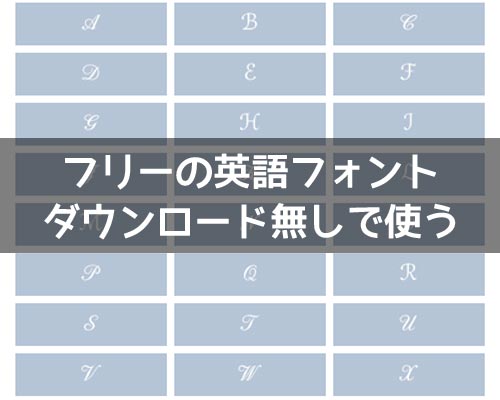
【フリー】英語フォントをダウンロードなしで使おう!オシャレなフォントも多数あります
英語フォントと聞くとフリーのフォントをダウンロードして利用するのを想像する方も多いですよね。
しかし最近ではダウンロードすら不要で英語フォントを使うこともできるのです。
特にツイッターやインスタなどのSNSなどで可愛い英語フォントやオシャレなフォントを使いたいと思っている方はダウンロードなんて必要ないんです。
英語フォントはダウンロード不要
【フリー】英語フォントをダウンロード不要で使おう!オシャレなフォントも多数あります
ダウンロードせずに英語フォントを使うのがどういう事かと言うと、絵文字のような感じでコピペして利用できるようになってます。
フォントをコピペするだけなのでダウンロードは不要。
好きなようにフォントを使うことができます。
どんなフォントが使えるの?
コピペで使える英語フォントにはどのようなフォントがあるのか気になる方もいるでしょう。
当サイトで確認しただけでも以下のような英語フォントがあります。
• 太字
• 太字斜体
• 斜体
• 明朝体
• 明朝体風
• ギリシャ文字
• ドイツ文字
• 花文字
• 筆記体
• 白抜き文字
• 手書き風文字
• 鏡文字
• 逆さ文字
上記の他にも様々なフォントがありますが、フォントの名前がわからないものも多いです。
最近流行の英語フォントとは?
最近人気の英語フォントと言えばやはり花文字のフォントでしょう。
花文字は筆記体のようなフォントなので名前などに使っている方も多いです。
通常のフォントよりもオシャレに見えるので名前の雰囲気を変えたいという方におすすめですね。
花文字は大文字が基本で小文字の場合は筆記体を使うのが良さそう。
オシャレな手書き風フォントも人気
また、花文字や筆記体などのフォントに加えて手書き風の英語フォントも意外と人気があります。
手書き風フォントは元々用意されているフォントではなく、手書きっぽい文字を探してa~zまで当てはめた文字です。
丸文字のようなやわらかい雰囲気の英語フォントを使いたい時には手書き風フォントを使うのが良いですね。
英語フォントをSNSで使う人が増えている
インスタのプロフィールや名前でオシャレな英語フォントを使っている人が多いですが、最近ではツイッターでも増えてきました。
ダウンロードしないでコピペだけで使える英語フォントは便利なので是非試してみると良いですよ。